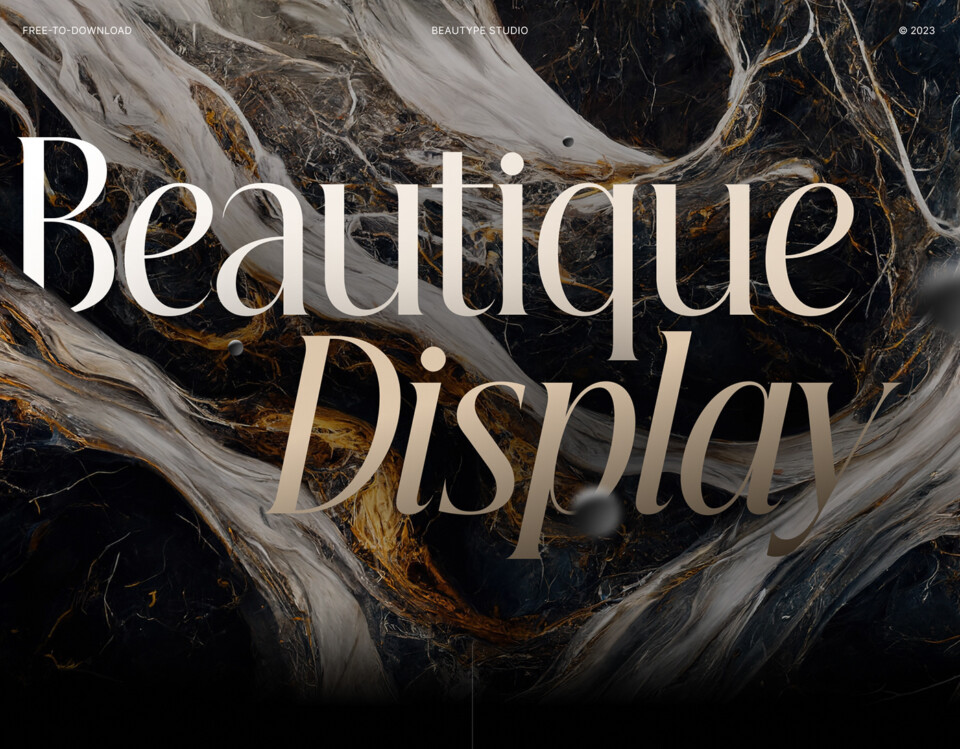
Giới thiệu về Font Tiếng Việt Beautique Display 1.1
Trong thế giới đồ họa hiện đại, việc lựa chọn một bộ Font Chữ phù hợp đóng vai trò quyết định đến tính thẩm mỹ của sản phẩm. Font Tiếng Việt Beautique Display 1.1 là một phiên bản nâng cấp hoàn hảo, mang đến vẻ đẹp thanh lịch và đầy nghệ thuật cho các dự án sáng tạo. Với đường nét thanh mảnh kết hợp cùng các chi tiết bo tròn tinh tế, bộ phông này giúp truyền tải thông điệp một cách lôi cuốn và chuyên nghiệp hơn bao giờ hết.
Đặc điểm nổi bật của bộ font
Phiên bản 1.1 không chỉ tập trung vào hình dáng mà còn tối ưu hóa khả năng hiển thị trên nhiều nền tảng khác nhau. Các ký tự được chăm chút tỉ mỉ, đảm bảo sự cân đối giữa các khoảng cách. Đây là lựa chọn lý tưởng cho những ai đang tìm kiếm phong cách thời trang, cao cấp nhưng vẫn giữ được sự gần gũi, dễ đọc.
Ứng dụng Font Tiếng Việt Beautique Display 1.1 trong học tập và công việc
Ngoài môi trường học đường, bộ phông này còn được ưa chuộng trong thiết kế logo, bìa sách và các ấn phẩm truyền thông xã hội. Nhờ tính năng Việt hóa chuẩn xác, người dùng không còn lo lắng về lỗi hiển thị dấu câu hay các ký tự đặc biệt trong tiếng Việt.